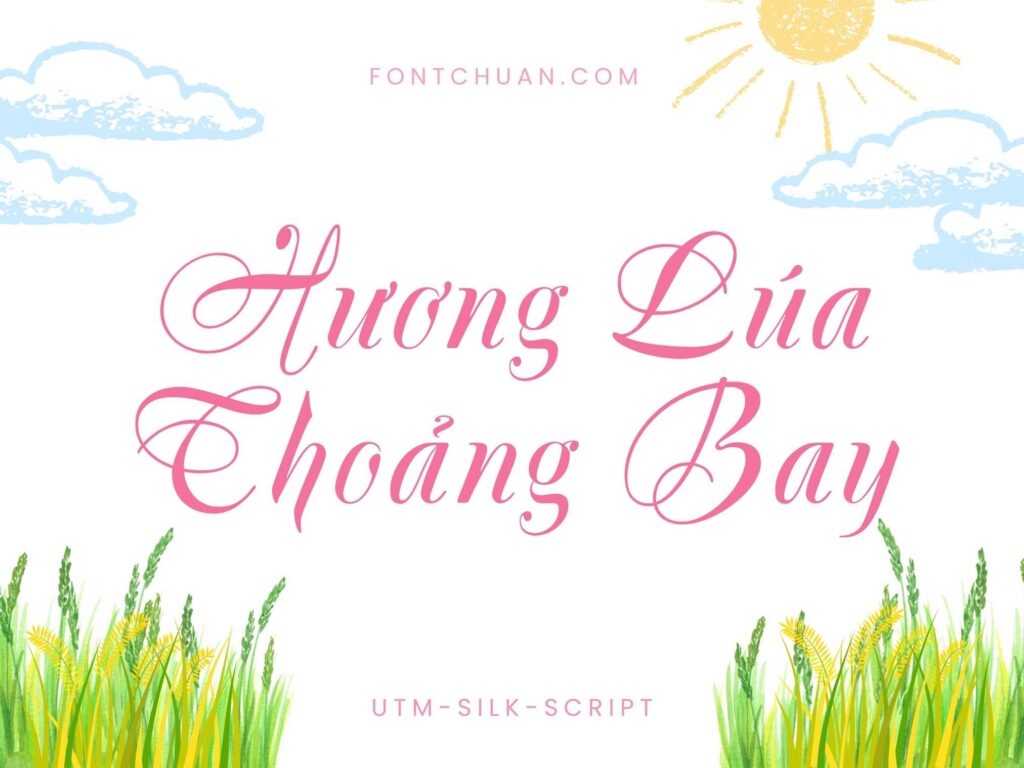
Font UTM Silk Script Việt Hóa
UTM Silk Script là một font chữ viết tay thanh lịch, thuộc bộ sưu tập font UTM. Với các đường nét mềm mại và uyển chuyển, font này mang lại cảm giác tinh tế và nghệ thuật cho các thiết kế. Đặc điểm nổi bật của UTM Silk Script là sự kết hợp giữa phong cách cổ điển và hiện đại, phù hợp cho các dự án như thiệp mời, tiêu đề sách, poster và các ấn phẩm nghệ thuật khác. Font này đã được Việt hóa bởi Thiên Minh, đảm bảo hỗ trợ đầy đủ các dấu và ký tự tiếng Việt, mang lại trải nghiệm sử dụng hoàn chỉnh cho người dùng. Ngoài tiếng Việt, UTM Silk Script còn hỗ trợ nhiều ngôn ngữ khác, mở rộng khả năng ứng dụng trong các thiết kế quốc tế. Thành viên của Font Chuẩn đã sưu tầm và giới thiệu UTM Silk Script đến cộng đồng thiết kế, giúp họ có thêm lựa chọn cho các dự án sáng tạo.
Nhờ các nét chữ mượt mà và liền mạch, UTM Silk Script cũng có thể được sử dụng như một Font chữ ký, lý tưởng cho các thiết kế logo cá nhân, thiệp cưới hay những ấn phẩm cần dấu ấn tinh tế và cá nhân hóa.
Với sự kết hợp giữa tính thẩm mỹ và khả năng ứng dụng cao, font này phù hợp cho các thiết kế thiệp cưới, tiêu đề sách, poster và các ấn phẩm nghệ thuật khác.
Tác giả: Tống Văn Hiệp
Việt hóa: Tống Văn Hiệp ( Tác Giả )